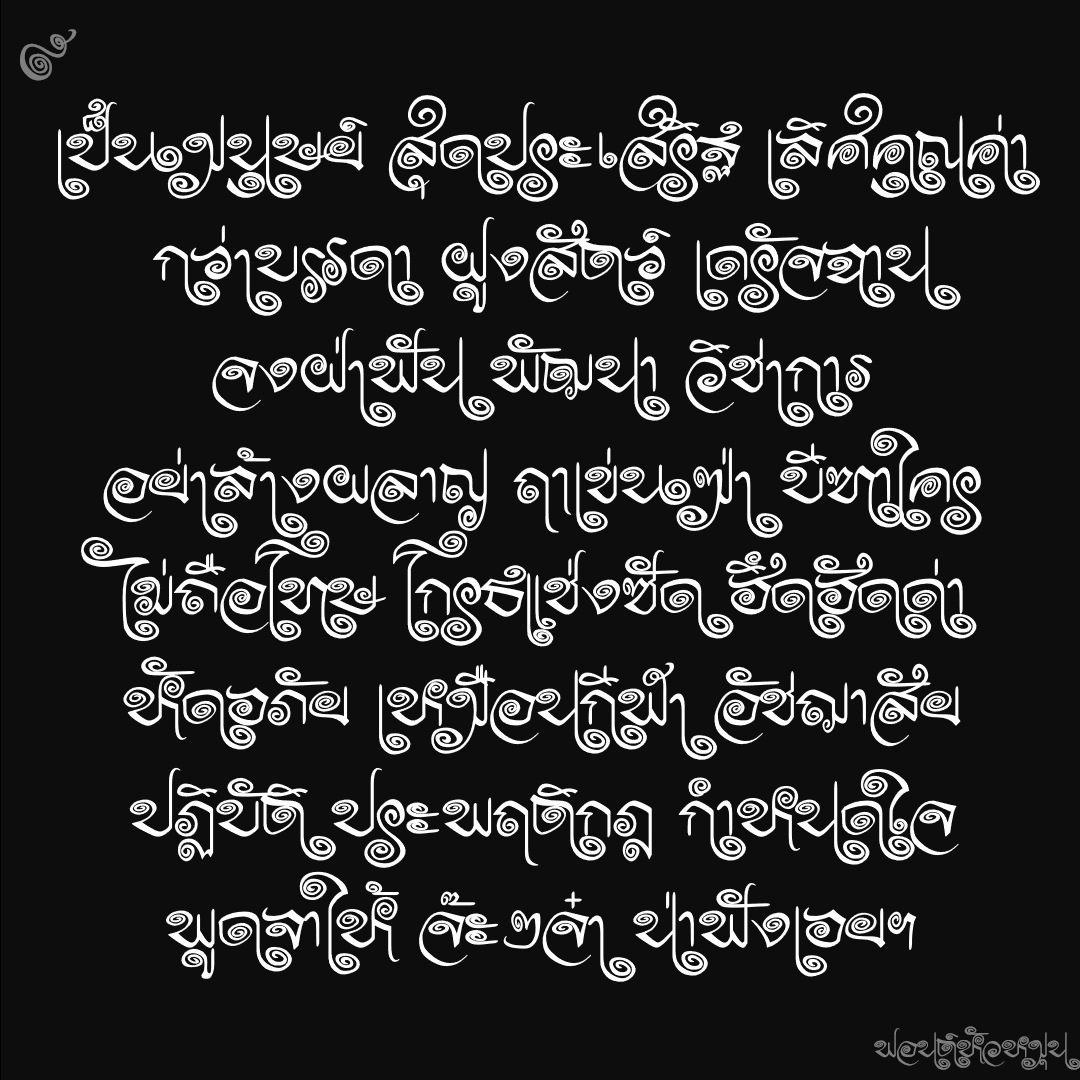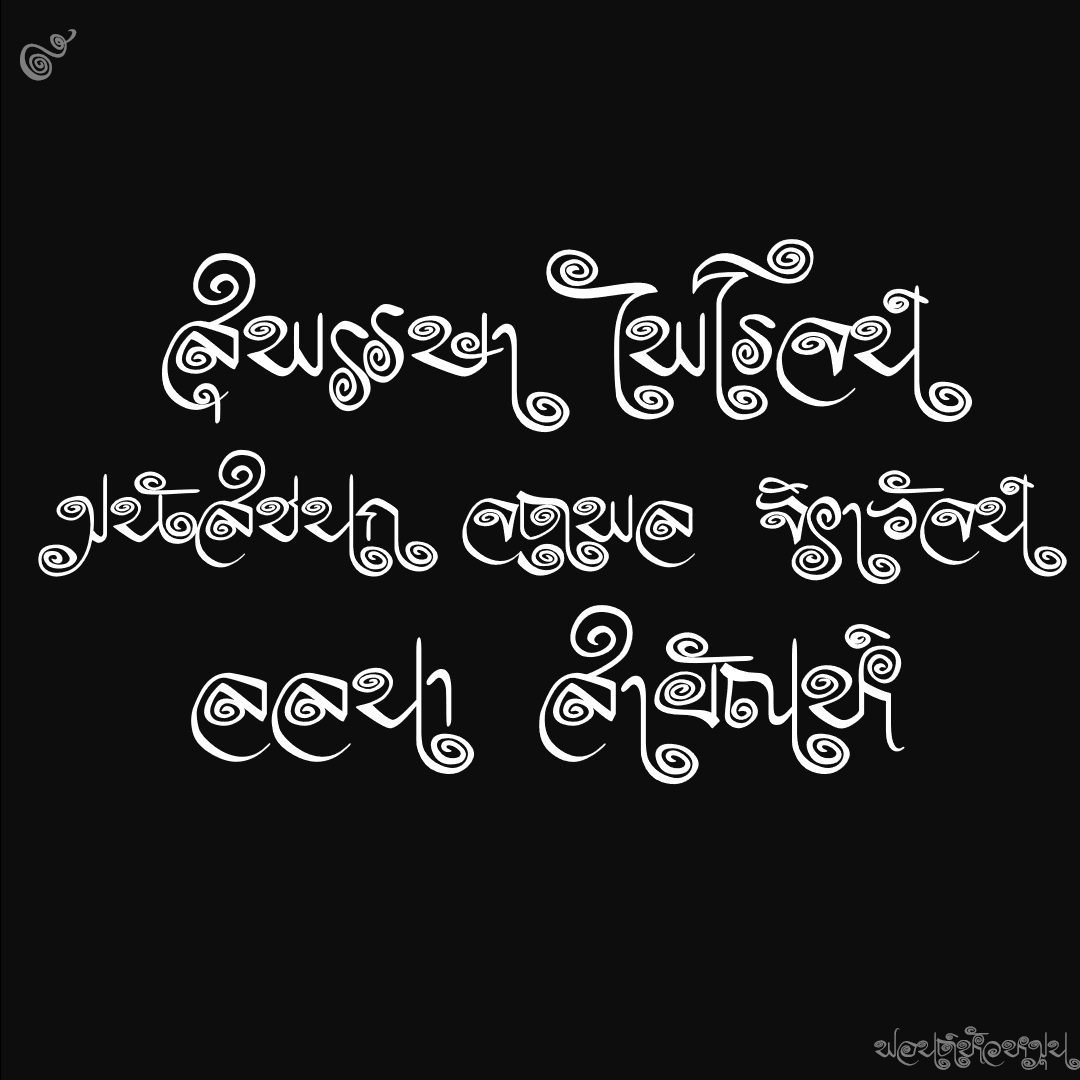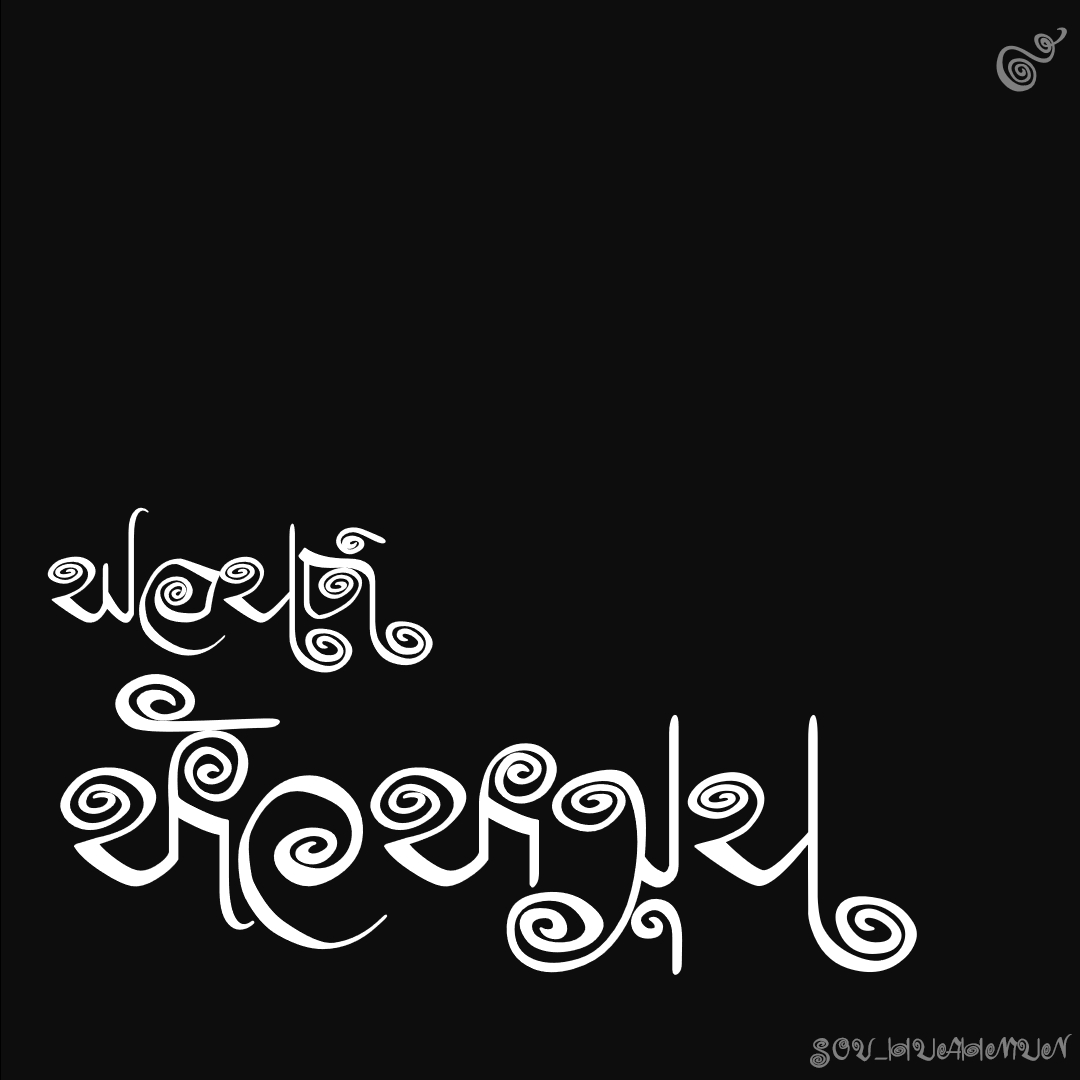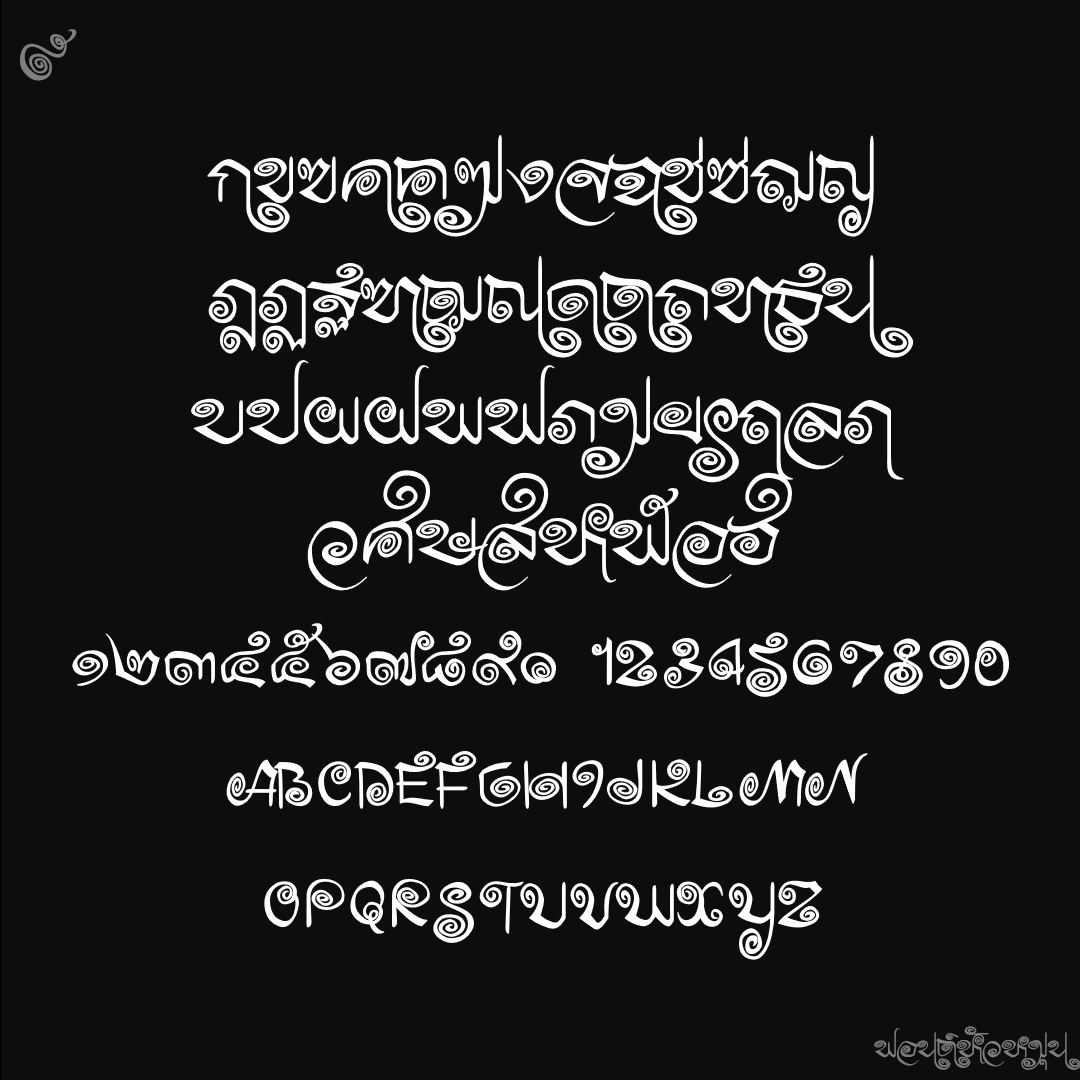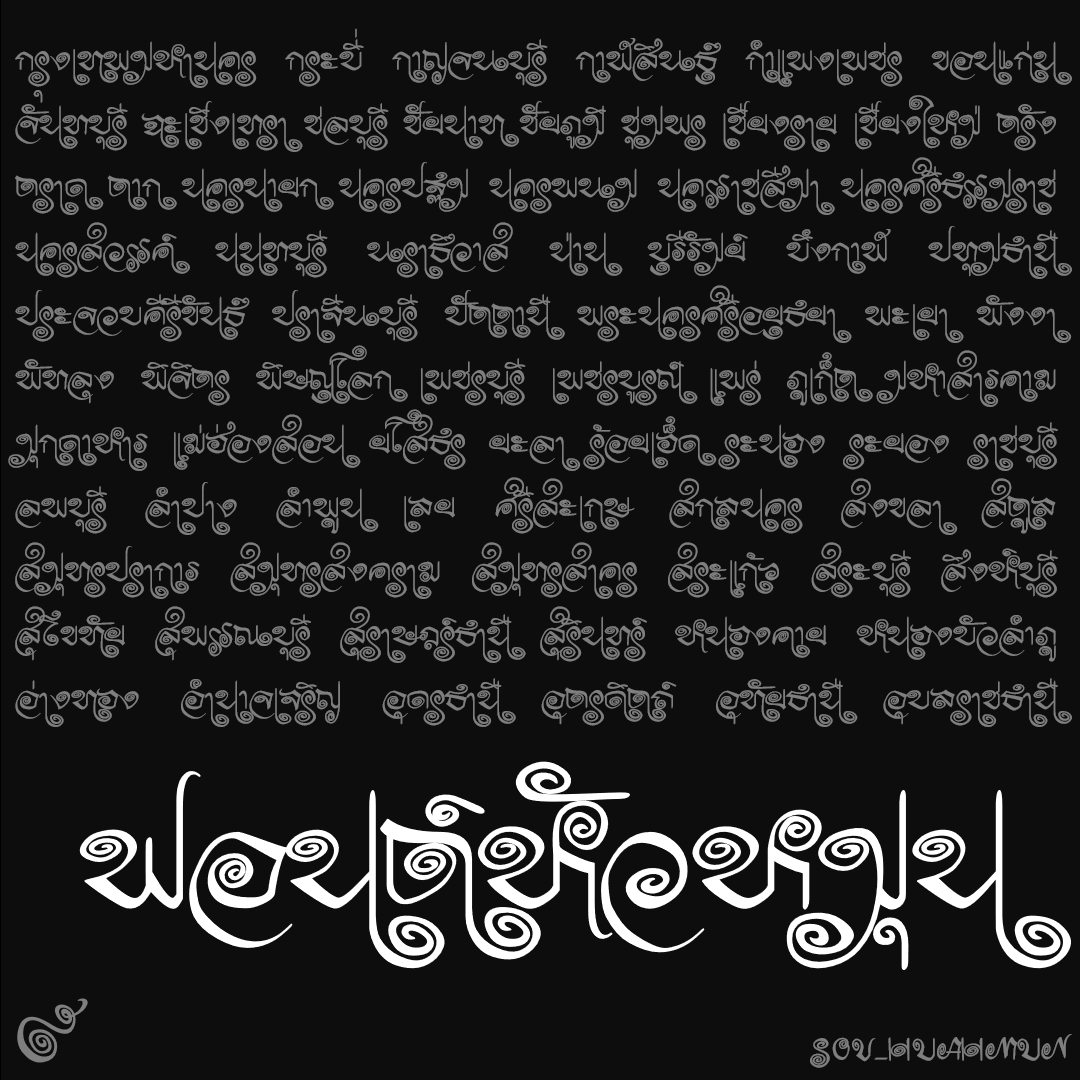
ฟอนต์ หัวหมุน
ฟอนต์หัวหมุน ต้นทางจากนิตยสารบันเทิงปีลึก นึกๆตอนทำก็หัวหมุนเพราะต้องแก้ปัญหาอักษรหมุนหัวมาทับกัน
ชื่อฟอนต์ : หัวหมุน
ฟอนต์หัวหมุน ต้นทางจากนิตยสารบันเทิงปีลึก นึกๆตอนทำก็หัวหมุนเพราะต้องแก้ปัญหาอักษรหมุนหัวมาทับกัน